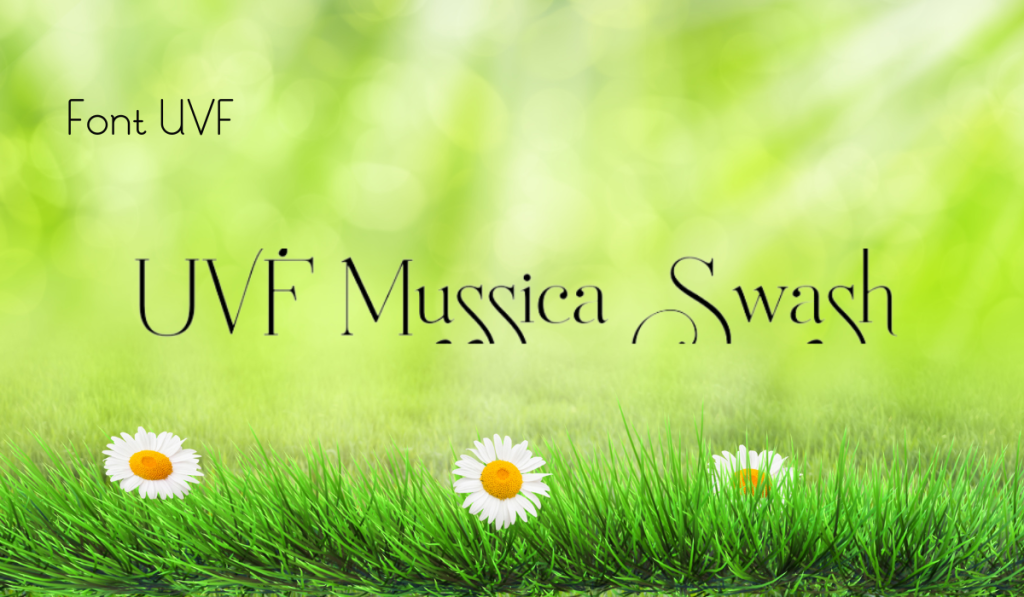
UVF Mussica Swash Font Việt Hóa
Tác giả: UVF
Bộ Font: UVF
Kiểu chữ: Chữ có chân
UVF Mussica Swash Việt Hóa là font chữ có chân với các đường nét cá tính và độc đáo, thuộc bộ font UVF. Font này được thiết kế nhằm mục tiêu tạo ra sự rõ ràng và dễ đọc, đặc biệt phù hợp cho các thiết kế như poster, logo, và tiêu đề. Đặc điểm hình dạng của UVF Mussica Swash là các đường nét đậm và tỷ lệ chữ cân đối, giúp tối ưu hóa không gian và tạo ấn tượng thị giác mạnh mẽ. Font này cũng đã được Việt hóa, mang đến sự linh hoạt và tiện dụng cho các dự án thiết kế bằng tiếng Việt, giúp người dùng dễ dàng tiếp cận và sử dụng.